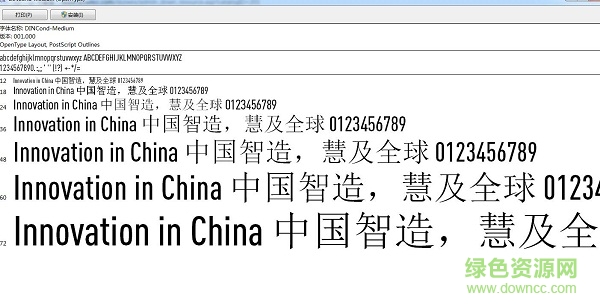
dincond mediumalternate
dincond-medium字體包收錄dincond medium-gbpc-euc-h和dincond mediumalternate兩款無襯線字體,該字體字距緊湊,線條粗細(xì)勻稱,起落筆干凈利落,喜歡的朋友快來下載吧!
dincond mediumalternate